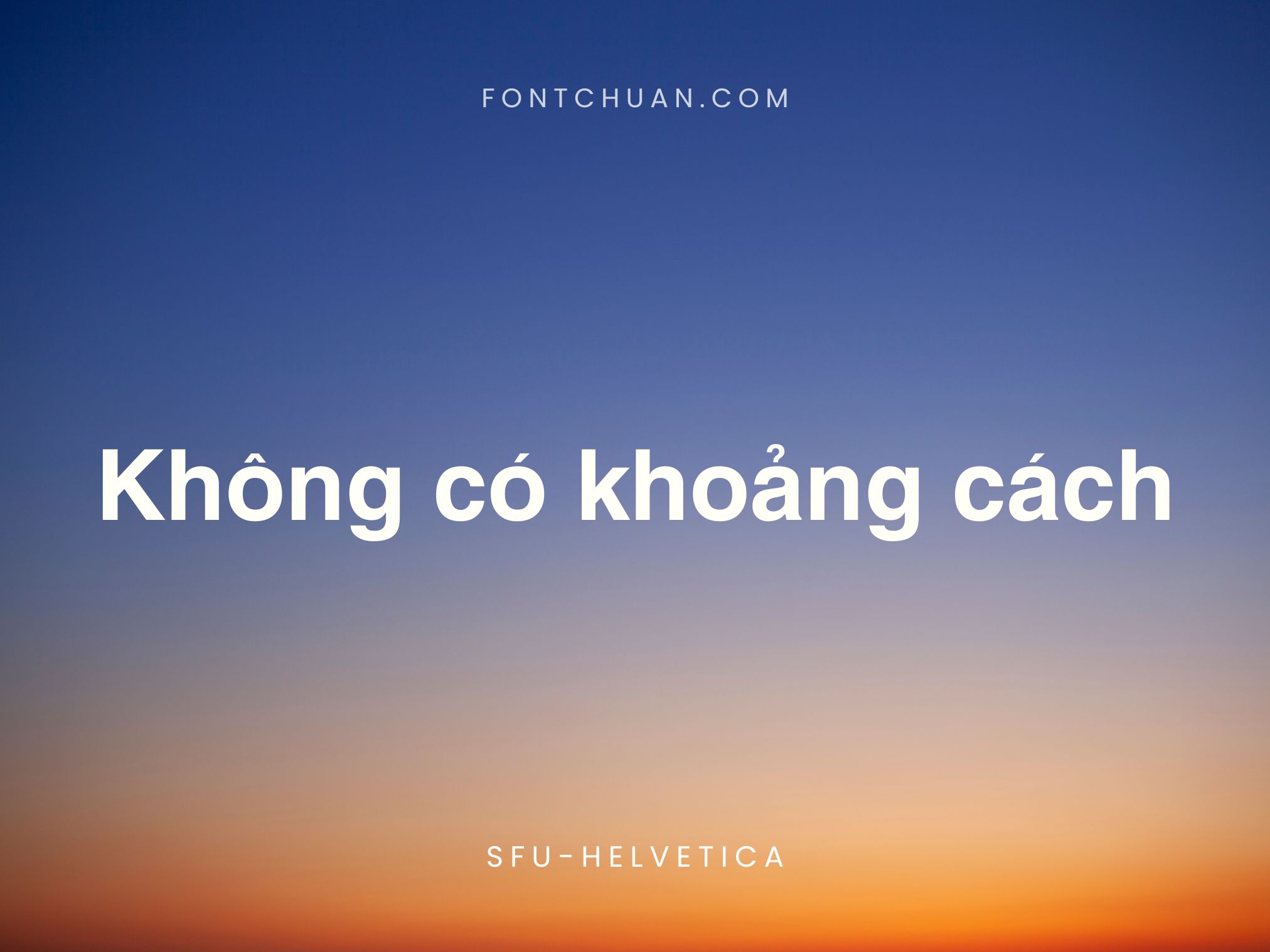
Helvetica là một kiểu chữ sans-serif được thiết kế bởi Max Miedinger và Eduard Hoffmann vào năm 1957 tại Thụy Sĩ. Ban đầu, nó được đặt tên là Neue Haas Grotesk và sau đó đổi thành Helvetica để phản ánh nguồn gốc Thụy Sĩ của nó. Font này được sưu tầm và đăng bởi thành viên của Font Chuẩn. Helvetica được thiết kế với mục tiêu tạo ra một kiểu chữ trung tính, rõ ràng và không mang ý nghĩa nội tại trong hình thức, phù hợp cho nhiều ứng dụng khác nhau.
Về mặt thiết kế, Helvetica nổi bật với chiều cao x lớn, các nét ngang và dọc kết thúc một cách rõ ràng và khoảng cách giữa các chữ cái chặt chẽ, tạo nên một diện mạo đặc và chắc chắn. Các đặc điểm này mang lại cho Helvetica sự đơn giản, sạch sẽ và dễ đọc, khiến nó trở thành lựa chọn phổ biến trong nhiều lĩnh vực thiết kế. Helvetica thường được sử dụng trong thiết kế đồ họa, nhận diện thương hiệu, biển hiệu và các tài liệu in ấn. Các ngành nghề như quảng cáo, công nghệ, giáo dục và bất động sản có thể tận dụng kiểu chữ này để tạo sự chuyên nghiệp và hiện đại trong truyền thông.